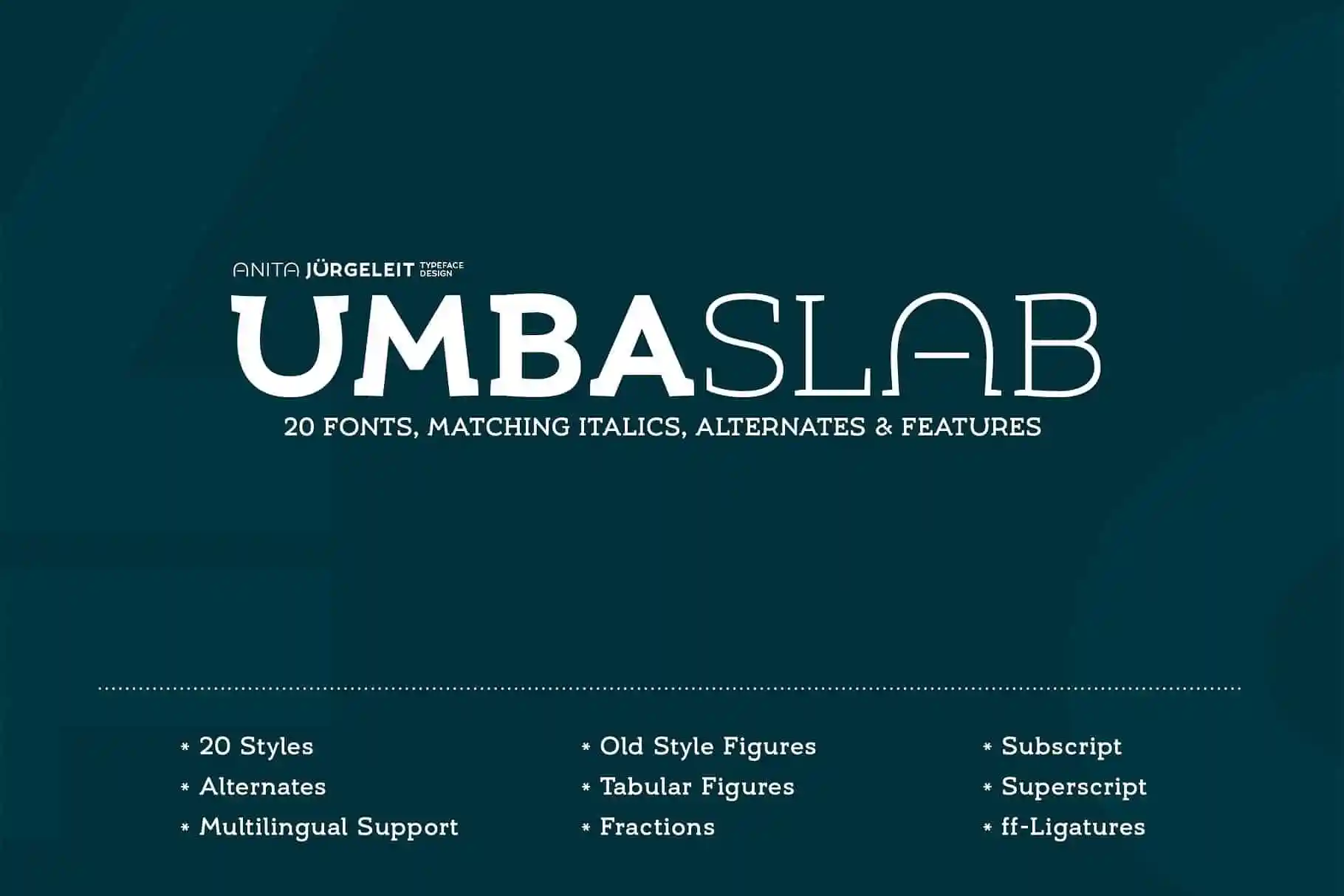
Umba Slab Font Family – Download Grátis
Olha aqui uma descrição atraente para a Umba Slab Font Family, criada pelo designer M.0Type. Esta fonte inclui 20 tipos diferentes e seu itálico complementar, tudo ideal para quem busca dar um toque de originalidade em projetos corporativos ou titulares. A Umba Slab é uma face tipográfica limpa e chamativa, mas que também transmite força e impacto. Criada pela talentosa Anita Jurgeleit, a famosa familia de fontes da Umba Slab incorpora elementos alternativos e fez-se conhecida por seu design versátil. Esteu tipo se destaca especialmente para criações em diversas categorias ou criação de marcas distintivas e titulares memoráveis. O design dinâmico entre as linhas finas e grossas faz da Umba Slab uma escolha inteligente para qualquer projeto, não importa a natureza do trabalho. Suas propriedades adicionam um toque único aos seus trabalhos, tornando-a uma opção favorita para designers que buscam expressar sua identidade visual de forma assertiva. Experimente a Umba Slab hoje e veja o impacto da sua força e elegância no seu design!